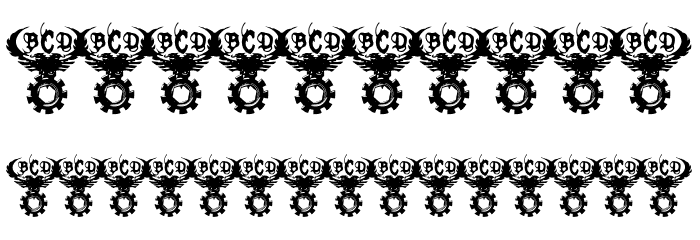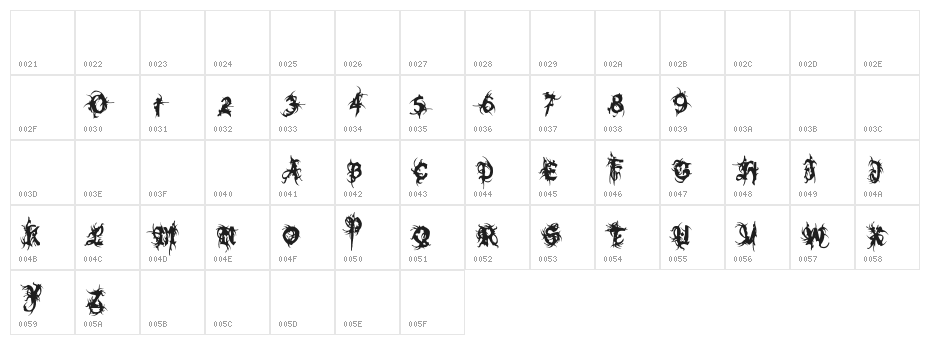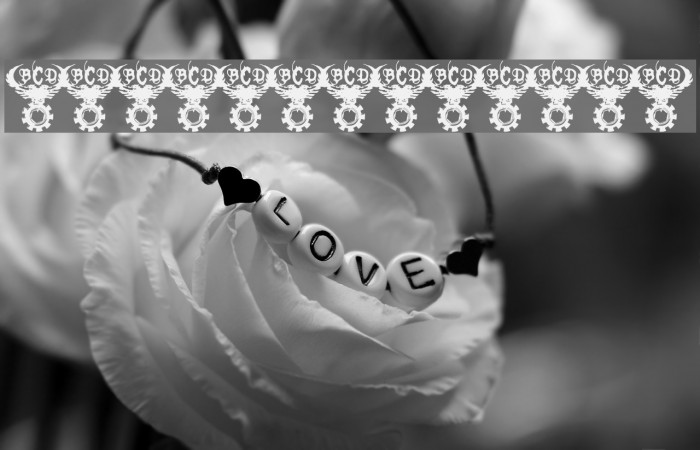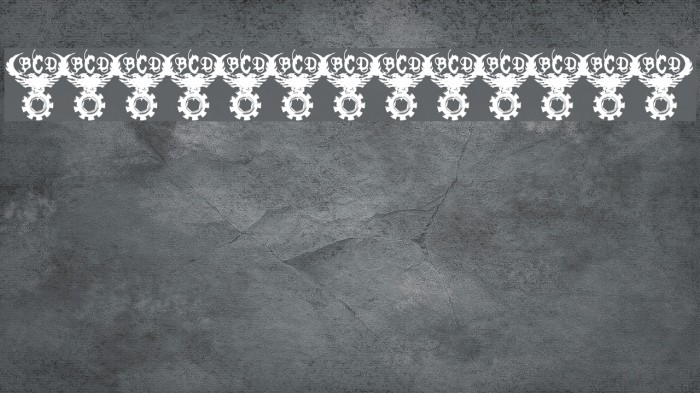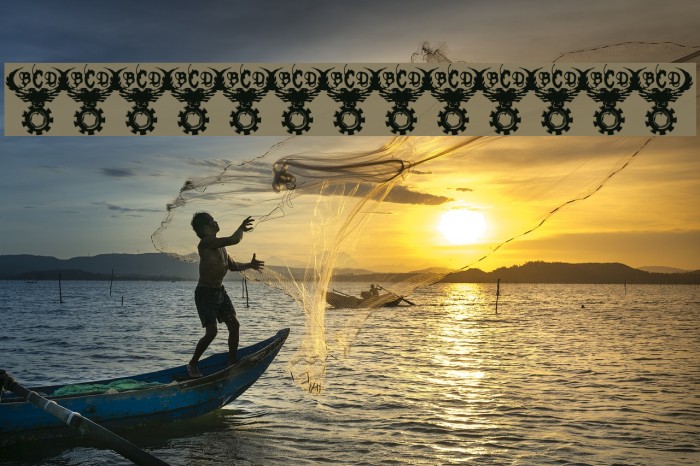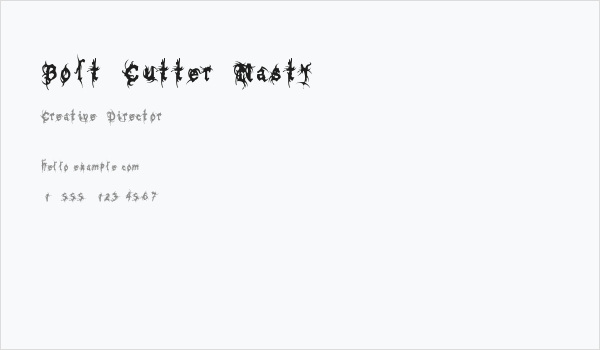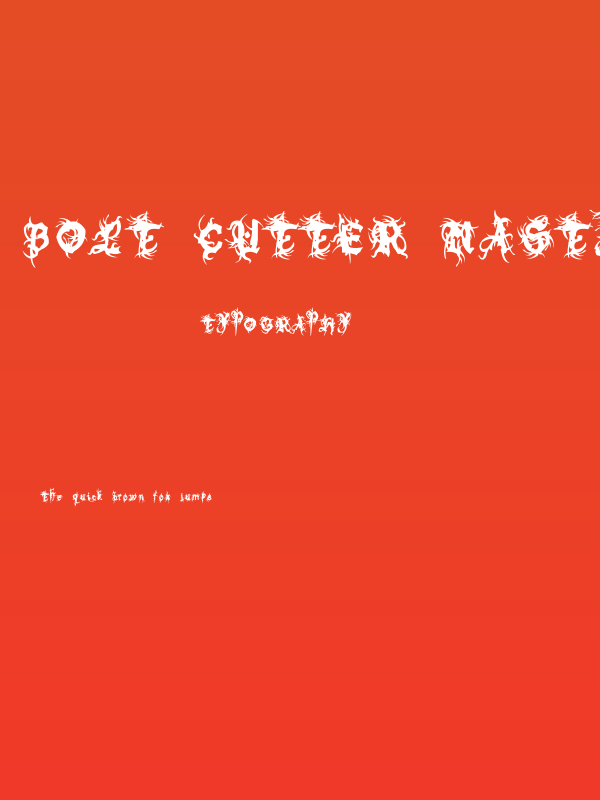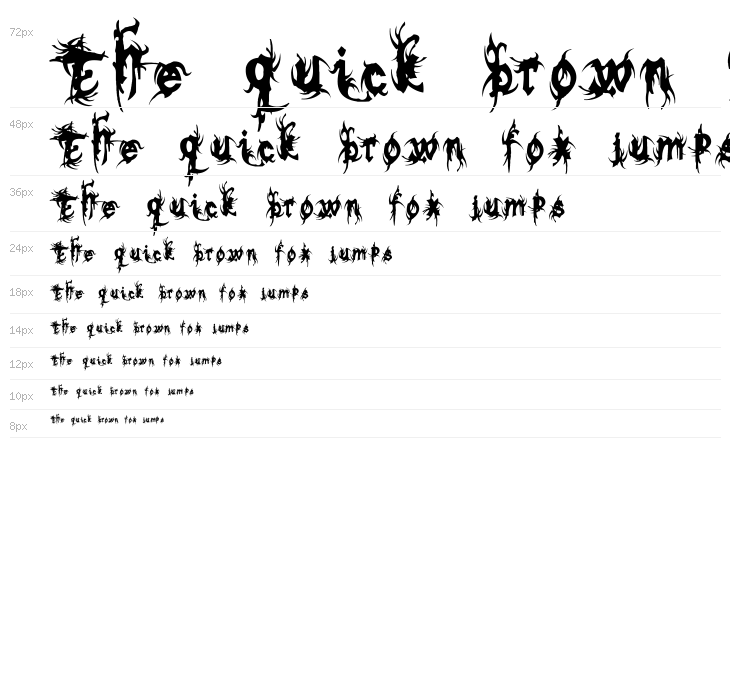
Bolt Cutter Nasty Font
| Kategorien | Gothic |
| Gesamtstil | Industrial, Gothic |
| Anwendungsfall | Logos, Posters, Album Covers |
| Vorgeschlagene Projekte | Ideal for use in branding for heavy metal bands, industrial-themed events, or as decorative elements in steampunk art projects. |